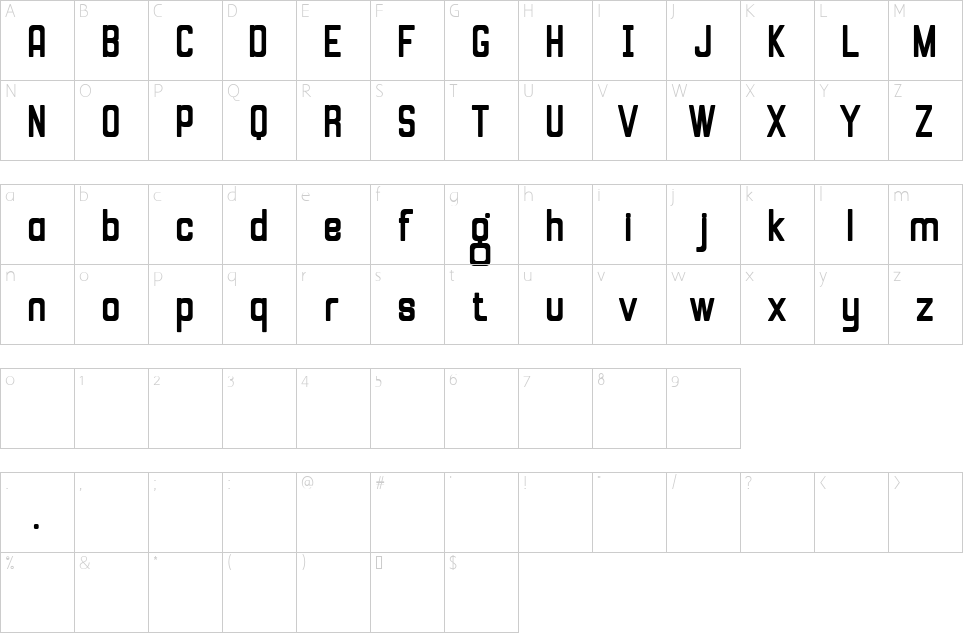
Astrionis é uma fonte que oferece uma experiência visual agradável e natural para quem procura uma fonte de graça. Desenvolvida pela Flawless And Co, Astrionis é ideal para qualquer projeto que busque uma aparência atraente e fluida. Com seu design cuidadosamente elaborado, a fonte se destaca por sua leitura confortável, tornando-a uma opção popular não apenas para designers e criadores de conteúdo, mas também para designers gráficos e profissionais de web. Sua elegância e facilidade de uso a tornam uma excelente escolha para qualquer projeto, garantindo que a sua mensagem seja transmitida com clareza e profissionalismo. Descarregada 947 vezes, essa fonte é reconhecida por seu design único e funcional. Não perca essa chance de adicionar um toque diferenciado a seus projetos com Astrionis.